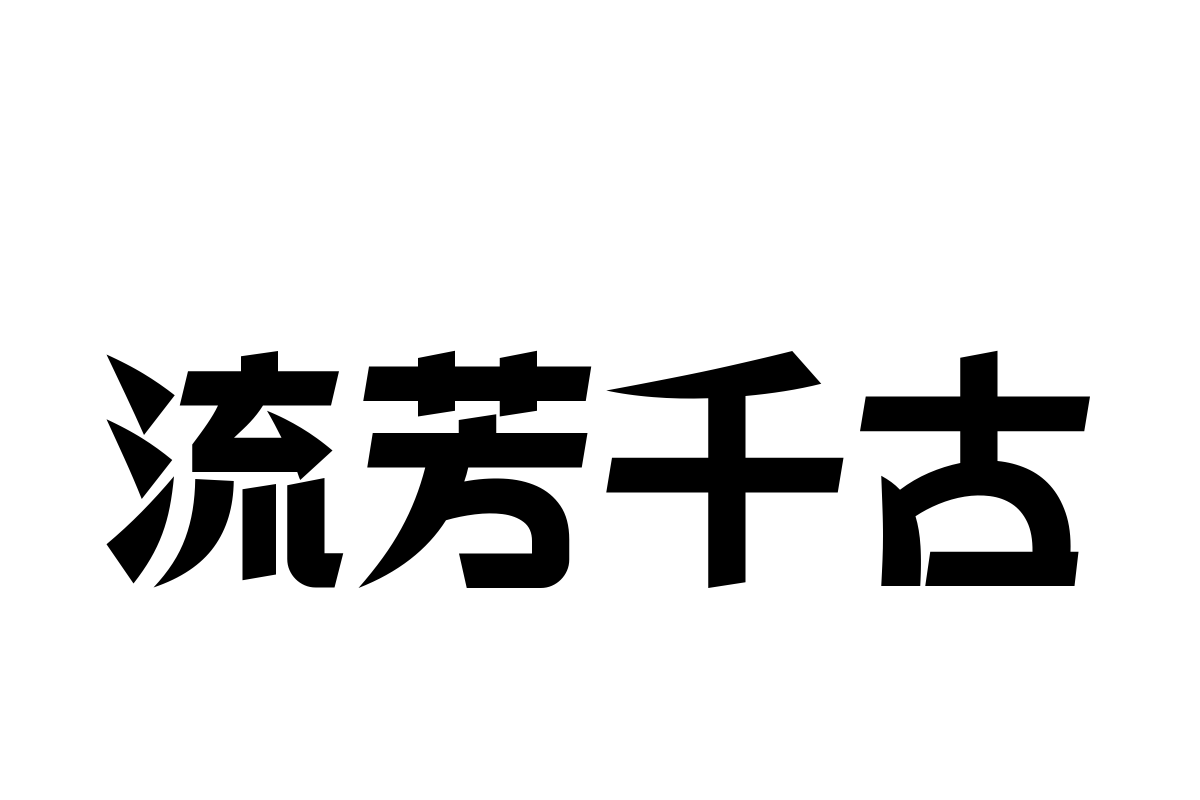
汉仪铸字乐淘是一款由汉仪公司开发的字体,具有独特的风格和特点。这款字体采用了现代简约的设计手法,线条流畅,字形简洁大方。在细节处理上,汉仪铸字乐淘注重字体的可读性和实用性,使得整个字体看起来既美观又实用。
汉仪铸字乐淘的主要特点是其独特的笔画结构和排版效果。这款字体的笔画流畅自然,线条粗细适中,给人一种轻松愉悦的感觉。同时,汉仪铸字乐淘的排版效果也非常出色,无论是标题还是正文,都能展现出一种优雅而不失活力的风格。
此外,汉仪铸字乐淘还具有一定的艺术性。这款字体在设计上融入了一些传统元素,如书法的韵味和装饰性的细节,使得整个字体更加具有个性和特色。这使得汉仪铸字乐淘不仅适用于商业用途,也适合用于个人作品的创作和展示。
总的来说,汉仪铸字乐淘是一款集美观、实用和艺术性于一体的字体,无论是用于印刷还是网络媒体,都能展现出其独特的魅力和价值。